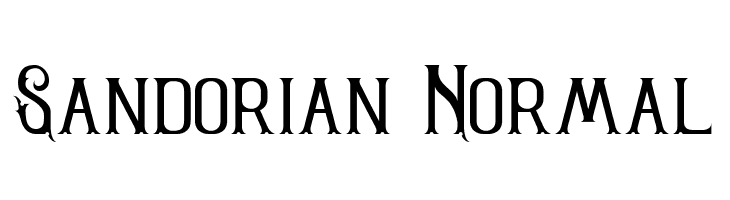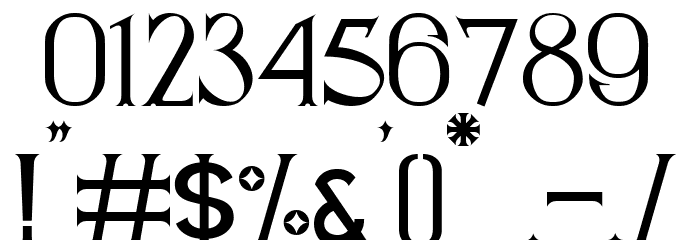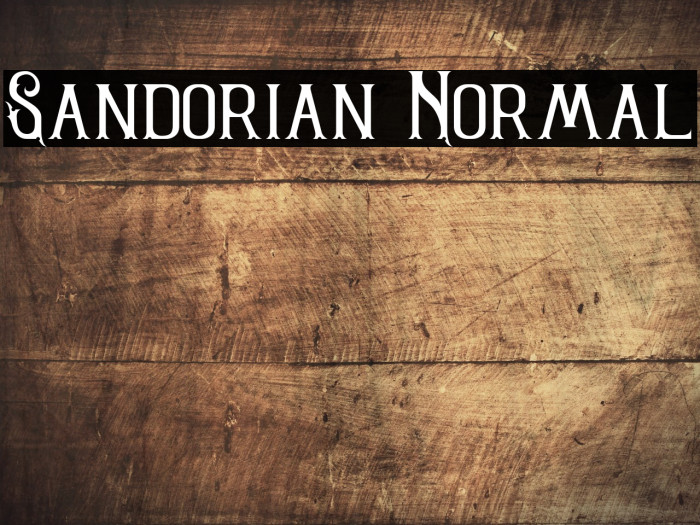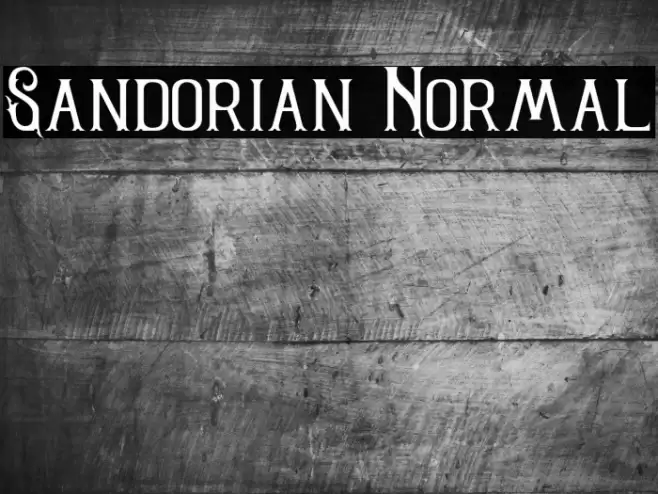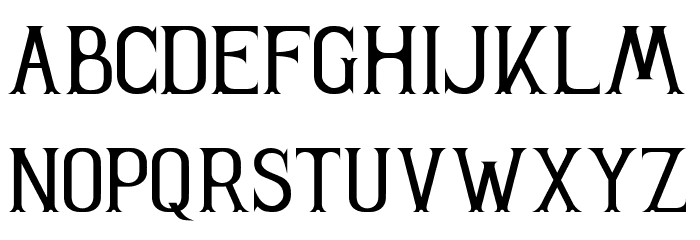
Sandorian Normal Font
| Caso d'uso | Headlines, Logos, Invitations |
| Progetti proposti | Ideal for branding, logo design, headlines, and invitations where a distinctive and artistic touch is desired. |